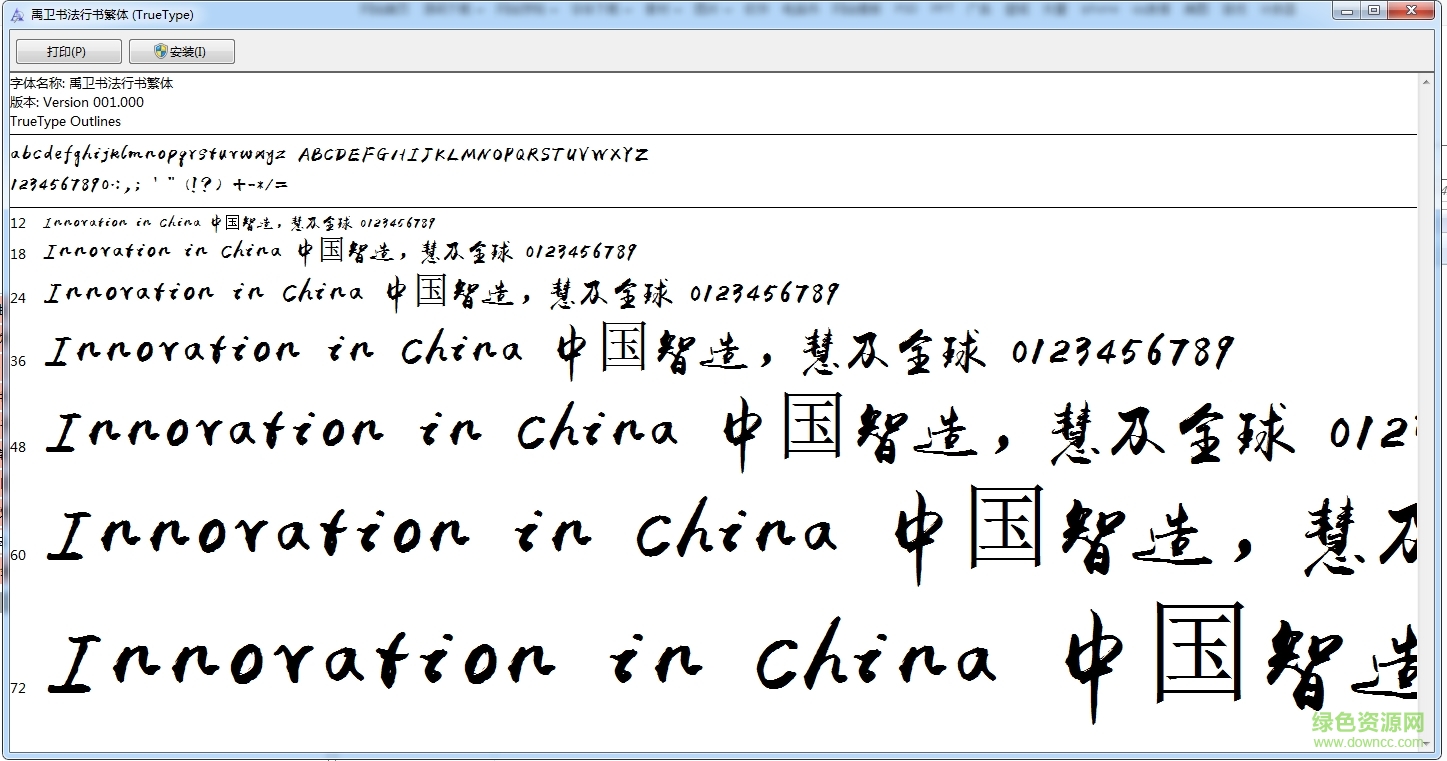
yuweijmfx字體又叫禹衛(wèi)書法行書繁體,是一款經(jīng)典的書法字體,風(fēng)格典雅,點(diǎn)畫呼應(yīng),線條流暢,清新優(yōu)美,常常用在文藝作品設(shè)計(jì)或是古典感興趣的朋友快來綠色資源網(wǎng)下載吧!
行書實(shí)用性和藝術(shù)性皆高,而楷書是文字符號(hào),實(shí)用性高而藝術(shù)性相對(duì)不足;相比較而言,草書則是藝術(shù)性高,但是實(shí)用性顯得相對(duì)不足。